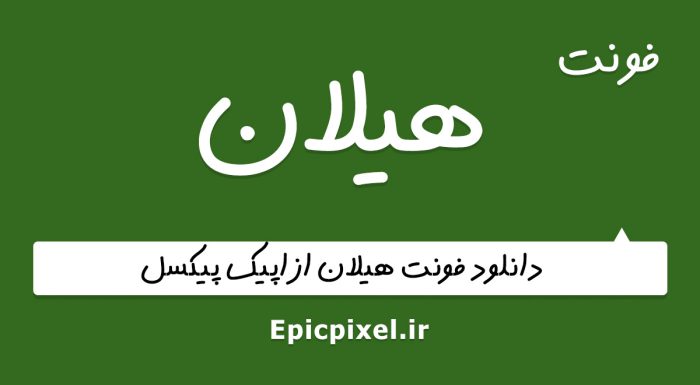
2 فونت هیلان فارسی
این فونت توی ظاهرش شبیه فونت های دستنویس هست و شاید اصلا درست هم همین باشه که تو این دسته بندی قراربدیمش اما ریزه کاری هایی که داره باعث میشه توی کلیت یه متن فرقش با بقیه فونت های هم رده خودش دیده بشه…